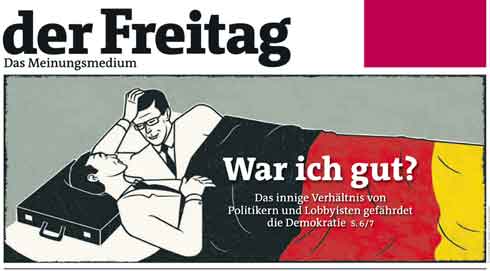
Alljährlich prämiert die Society for News Design (SND) Mitte Februar die am besten gestalteten Tages- und Wochenzeitungen weltweit. Vergangenes Jahr war nicht einfach für die Branche, was auch die Jury spürte. Fast überall kämpfen die Zeitungen mit schwindenden Auflagen und sinkenden Anzeigenerlösen. In den USA scheint die Situation dramatischer als außerhalb, wo die Printmedien nach Auffassung der SND-Berater einen »gesünderen« Eindruck machten.
Doch gerade der Wettbewerb mit den digitalen Nachrichtenquellen sei eine große Herausforderung für die Gestaltung. Die Rolle es Designers habe sich gewandelt, die visuelle Inszenierung sei wichtiger als je zuvor. »This is the age for the thoughtful designer. Your efforts must be as considered as they are creative.« resümieren die Experten bei SND.
Dieses Mal beteiligten sich 240 Zeitungen am Design-Wettbewerb der SND. Sie reichten das nach ihrer Ansicht beste Exemplare des vergangenen Jahres ein – drei eingebettete Flickr-Diashows im nachfolgenden Beitrag (mit Full-Screen-Funktion) zeigen diese eingereichten und prämierten Ausgaben.
Am 8. Februar entschied sich die Jury für drei Sieger, von denen zwei aus Deutschland kommen, was das gefühlte hohe Niveau des deutschen Zeitungsdesigns bestätigt:
1. der Freitag (Wochenzeitung, Berlin)
2. Frankfurter Allgemeine Sonntagszeitung (Wochenzeitung, Frankfurt am Main)
3. The New York Times (Tageszeitung, New York, USA)
Die Zeitungen wurden gewählt, weil ihre Gestaltung beweist, dass die Redaktionen ihre Leser genau kennen und gut bedienen möchten. Das Aussehen der Siegerblätter ist in jedem einzelnen Fall das Ergebnis einer sorgfältigen Planung plus einer redaktionellen Strategie, die sich von der ersten bis zur letzten Seite durch das Gedruckte zieht. Die Jury: »They each have a strong DNA — an identity that goes beyond format. A partial inside page is as identifiable to the publication as its’ page one.«
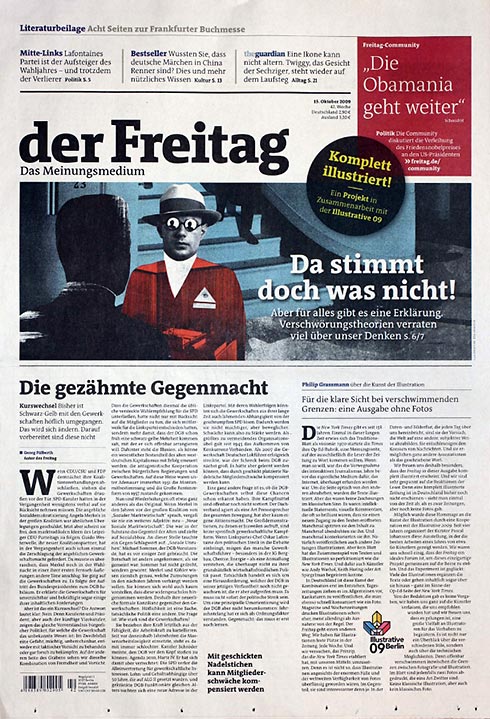
Der Freitag, Berlin, wöchentlich, Auflage 12.400 Exemplare
Wie die Berliner Wochenzeitung gestern in ihrem Redaktionsblog mitteilt, habe die Freitag-Redaktion nach Erreichen der Nachricht aus Orlando, Florida, erst mal die Arbeit für ein paar Minuten eingestellt: »Die Freude ist riesengroß«. Verantwortlich für die vorbildliche Gestaltung des Blattes sind Matthias Last und Alexander Seeberg-Elverfeldt, das interne Art-Department (Janine Sack, die Leiterin, Andine Müller, Corinna Koch, Jana Schnell und Stefan Stalder) sowie Anja Horn und ihr Team beim Berliner Designbüro Einhorn Solutions. Johannes Erler (factordesign) stand beim Redesign beratend zur Seite. Und nicht zuletzt gebührt dem Schriftentwerfer Luc(as) de Groot ein Lob, der für dieses Projekt eine weiterentwickelte Version von TheAntiqua produzierte.
Hier die ausführliche Begründung der Jury, übersetzt von Christine Käppele bei Freitag: »Auffällig und doch so schlicht. Seite für Seite wartet diese Zeitung jede Woche mit visuellen Überraschungen auf; diszipliniert und elegant, anstatt laut und chaotisch. Wie gelingt dem Freitag diese schwierige Balance? Das strenge Grundlayout – eine solide Typographie, eine intuitive Navigation – wird durch eine präzise Auswahl und Präsentation der visuellen Inhalte ergänzt. Die Zeitung, die 2009 radikal neu gestaltet wurde, hat von der Titelseite an keine Angst davor, auffällige, originelle Illustrationen zu zeigen. Ein Frosch, der in allen Regenbogenfarben schillert, sticht dort hervor, als wolle er den Leser dazu auffordern, in die Zeitung einzutauchen. In der Mitte einer Doppelseite illustriert das wundervolle Foto eines einsamen Iglus in der gefrorenen Tundra eine Leseprobe auf eindringliche Art. Farbe wird zur Navigation des Lesers sparsam und strategisch eingesetzt. Woche für Woche ist die Struktur einheitlich, ohne dass die Zeitung dadurch vorhersehbar wird. Ähnlich reduziert ist die Typographie. Verwendet wird nur eine Schrift, was jedoch durch den Einsatz verschiedener Schriftschnitte nie eindimensional wirkt. Es gibt keine Unordnung oder unnötige Bilder, die den Blick ablenken. Der Freitag scheut sich nicht davor, seine Leser einfach lesen zu lassen. Um es kurz zu machen: Die Zeitung ist ein Genuss«.
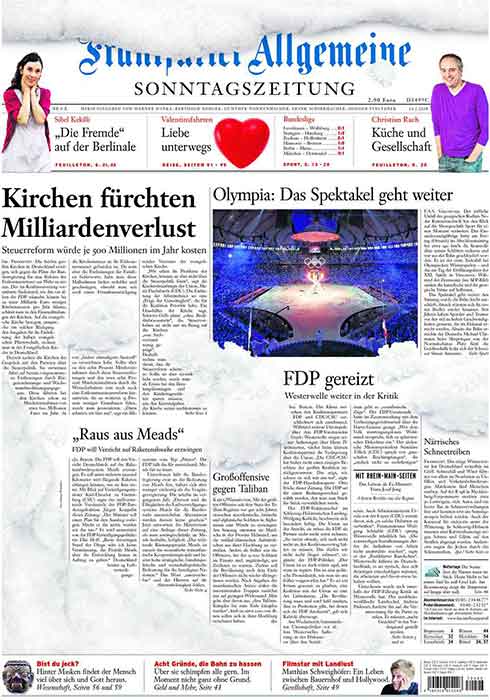
Frankfurter Allgemeine Sonntagszeitung, wöchentlich, Frankfurt, Auflage 347.000 Exemplare
Die Frankfurter Allgemeine Sonntagszeitung (FAS) ist die Sonntagsausgabe der FAZ, ursprünglich nur als Regionalzeitung in der Region Rhein-Main vertrieben, und seit dem 30. September 2001 bundesweit erhältlich. Trotz der gemeinsamen Nutzung redaktioneller Ressourcen (die FAS hat aber zusätzlich 50 eigene Redakteure) tritt die Sonntagszeitung eigenständig auf. Ihr Erscheinungsbild unterscheidet sich deutlich vom Muttermedium in der Satzgestaltung, der durchgängigen Vierfarbigkeit und einer eigenen Brotschrift, der Janson. Außerdem ist ihr Ton leichter und unterhaltsamer als jener der seriösen FAZ. Ein Erkennungsmerkmal sind die oft eingesetzten Illustrationen am Artikelanfang (Vignetten), die unter anderem von dem Illustrator Bengt Fosshag stammen.
Die Jury: »Ein bemerkenswerter Mix visueller Elemente entfaltet sich auf den Doppelseiten dieser Wochenzeitung im Nordischen Format. Anstatt Geschichten in unveränderbare Layouts zu quetschen, erzählen die Designer des Sonntagsblatts – handwerklich gekonnt – Geschichten, passend zum Thema des Beitrags. Auf einer Seite ließ sich eine Geschichte am besten mit 24 Screenshots vom iPhone illustrieren. Wenige Seiten später erlaubt die riesige Abbildung eines Renaissance-Gemäldes dem Leser, sich in malerischen Details zu verlieren, was die begleitende Geschichte zusätzlich kraftvoll unterstützt. Der sinnvolle Gebrauch weißer Flächen und des Rasters, verbunden mit dem umsichtigen Einsatz von Farbe tragen zur allgemeinen Klarheit bei. Das Ergebnis: eine Zeitung, welche die Zeit, den Verstand und die Neugier standhaft respektiert«.
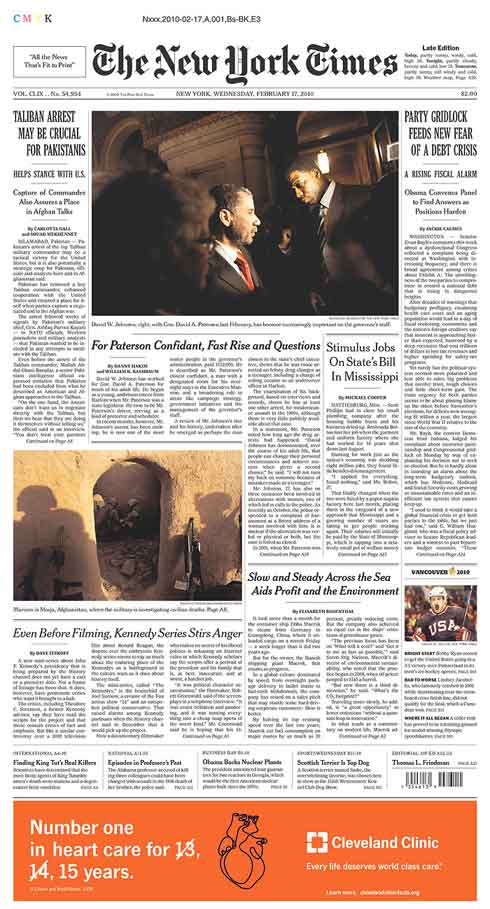
The New York Times, täglich, New York City (USA), Auflage 930.000 Exemplare
Die New York Times (NYT), gegründet 1851, ist eine einflussreiche überregionale US-Tageszeitung, die von der New York Times Company geführt wird. Sie wird auch »The Gray Lady« genannt. Ende 2004 betrug die verteilte Druckauflage wochentags 1.124.700 Exemplare, heute liegt sie bei 930.000. Die Wirtschaftskrise ab 2008 traf die New York Times mit Einbrüchen bei den Anzeigeneinnahmen. Am 19. Januar 2009 teilte die New York Times Company mit, dass sich der mexikanische Milliardär Carlos Slim mit weiteren 250 Millionen Dollar am Verlag beteiligt. Die Redaktion wurde von 1330 auf 1100 Mitarbeiter reduziert. Wie schon andere Druckpublikationen auch verlegt die NYT den Schwerpunkt ihrer Aktivitäten zunehmend in den Online-Bereich, der zunächst als Ableger und Ergänzung der Druckausgabe behandelt wurde. Zuletzt machten die New Yorker mit innovativen Apps und Webseitenkonzepten auf sich aufmerksam.
Die Jury: »A large-circulation general-interest newspaper is a tough beast to visually tame. Every Sunday, the local edition of The New York Times has a dozen or more sections, covering the world from Bali to the Bronx, and topics ranging from nuclear bombs to nose jobs. A DNA of visual discipline binds sections with distinct accents together into a paper that speaks with one voice. A design architecture of timeless elegance provides a solid foundation upon which to build innovative visual storytelling that weaves through the paper. In the Metropolitan section, the extraordinary lives of ordinary people unfold in a feature that raises the bar for photo columns. When it comes to presenting long-form written journalism, Times designers realize their job is to enhance the pleasure of reading narrative text, not diminish it with distractions. From its iconic front page to cutting-edge fashion photos in its magazine, the Times serves a national audience with a sprinkle of New York flavor.«
Der Freitag ist ein bisschen zu Links für ein gutes Anzeigengeschäft.
Zum Einen gibt es den Freitag nicht nur in Berlin, sondern an so ziemlich jedem Bahnhofskkiosk in Deutschland (außer in Bayern).
Zum Andern erschlagen ja weniger die Anzeigen in den anderen Zeitungen, sondern vielmehr die Zeitungen selber. Die eingeschneite FAS ist da ja noch sehr zurückhaltend. Eine einzige Seite mit 14 (vierzehn!) verschiedenen Linien wie manchen tags die Berliner Zeitung, da rennt man doch weg. Und man findet vor lauter Bildern ohne Sinn den Artikel gar nicht mehr.